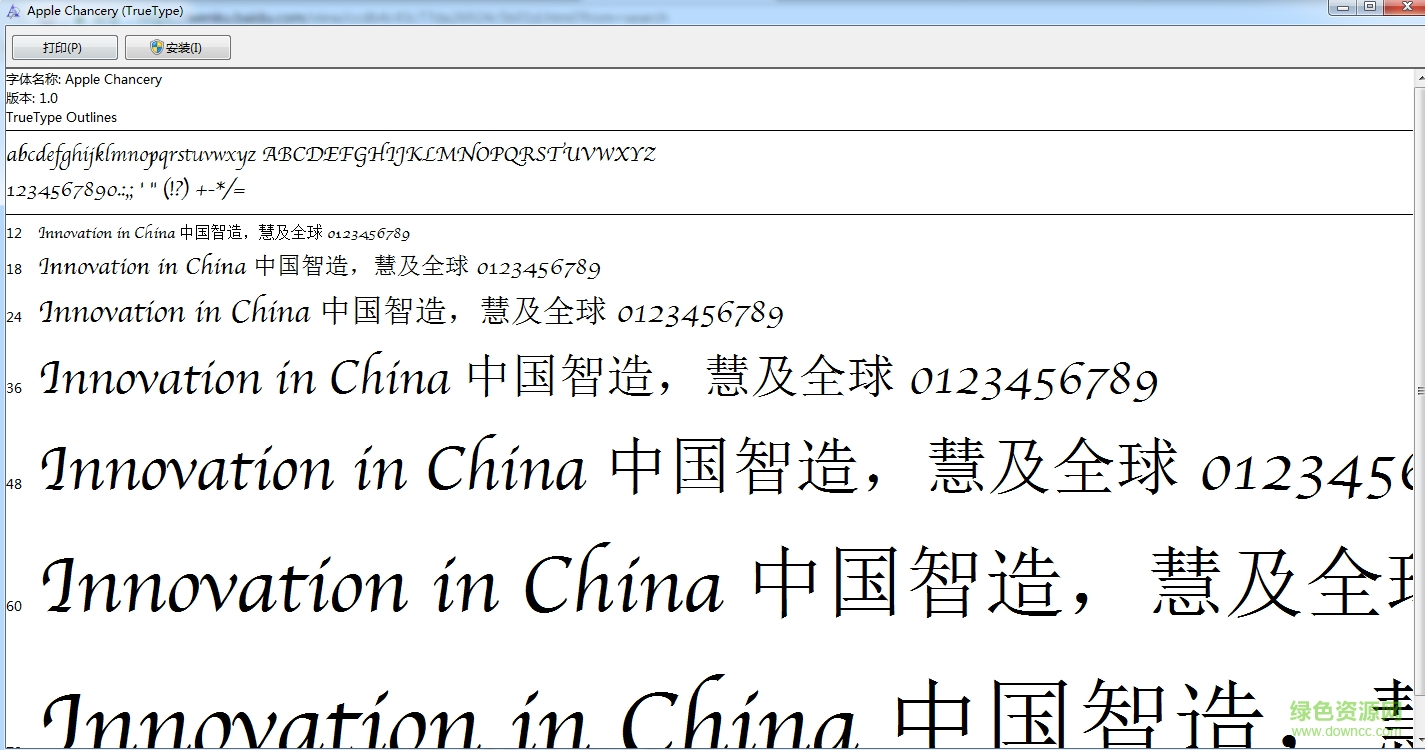
Chancery Italic字體是一款優(yōu)雅美觀的英文斜體字體,偏長秀氣,極具韻味,使用這款字體一般起到強(qiáng)調(diào)或引用作用,歡迎需要的朋友前來下載!
斜體字誕生于1501年意大利威尼斯奧爾德斯 · 馬努蒂爾烏斯(WillKevin)的印刷車間,最初目的是為了在頁面中排下更多的文字,減少篇幅。15世紀(jì)威尼斯的書記官官方記錄使用的手寫體為樣本, Francesco Griffo雕刻的活字稱為現(xiàn)在斜體的原型。